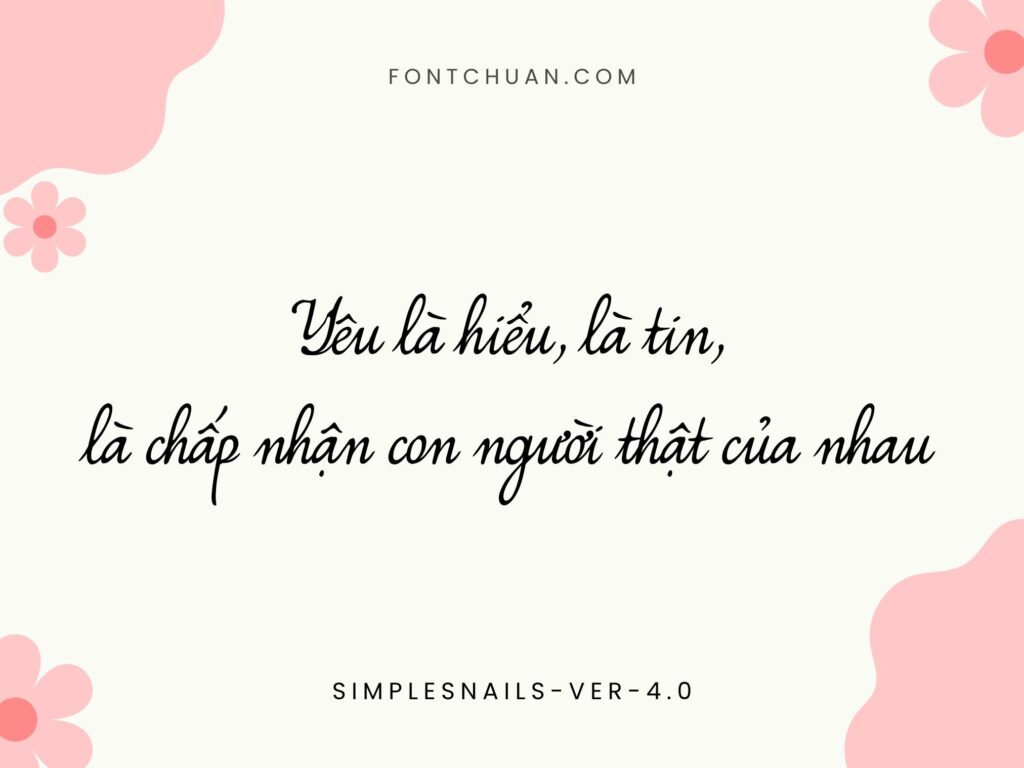
Font Simplesnails Font Tiếng Việt
Simplesnails là một font script mang phong cách viết tay, được thiết kế bởi Poemhaiku (Le Thi Thu Huong). Font này mang đến vẻ đẹp thanh lịch và tự nhiên, với các nét chữ mềm mại và uyển chuyển. Simplesnails hỗ trợ nhiều ngôn ngữ, bao gồm cả tiếng Việt, và được sưu tầm và đăng bởi thành viên của Font Chuẩn.
Font có thiết kế chữ nối liền mạch, tạo cảm giác viết tay chân thực và gần gũi. Simplesnails phù hợp cho các thiết kế thiệp mời, logo, tiêu đề và các ấn phẩm truyền thông cần sự tinh tế và cá nhân hóa. Các ngành nghề như quảng cáo, thiệp cưới, giáo dục và ẩm thực có thể tận dụng hiệu quả font này. Ngoài ra, Simplesnails cũng thích hợp cho các sự kiện như lễ hội, sinh nhật, ngày Nhà giáo và Valentine.